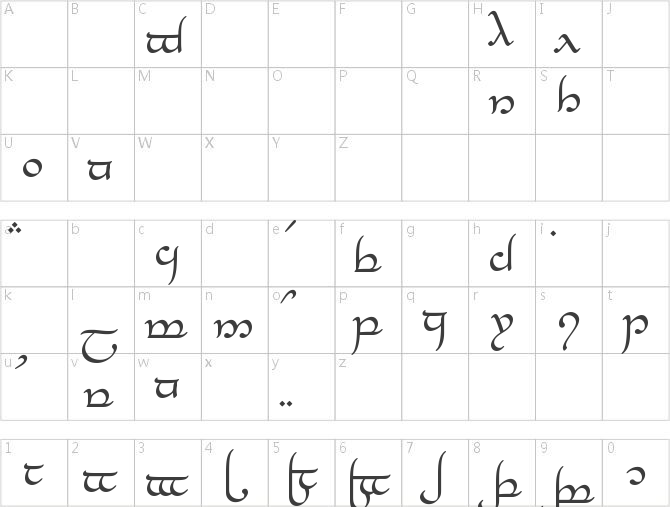
字體名稱: Tengwar
Tengwar-Elesil-Medium
Tengwar-Elesil-Medium介紹
Tengwar-Elesil-Medium字體字庫是一款讓人賞心悅目、百看不厭的英文字體,適合各類廣告和產品包裝設計應用,字體大小0.02MB,格式為ttf字體,上傳用戶是隨緣゜,作者/版權方為未知
Tengwar-Elesil-Medium效果圖